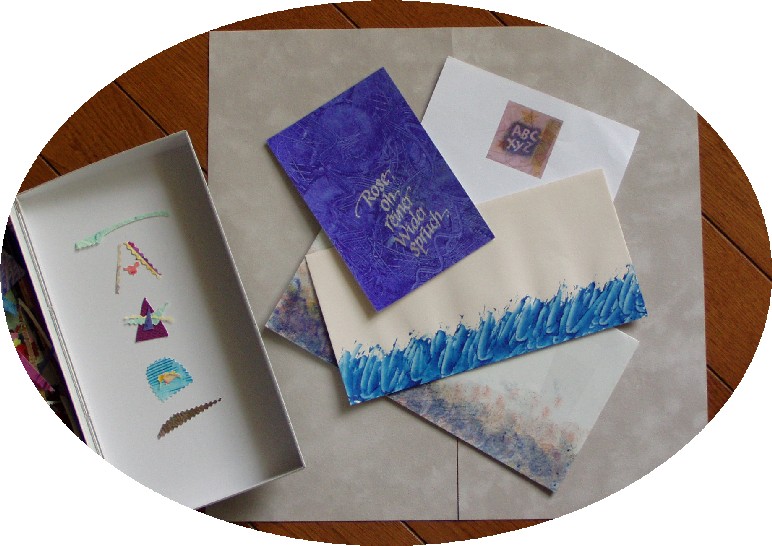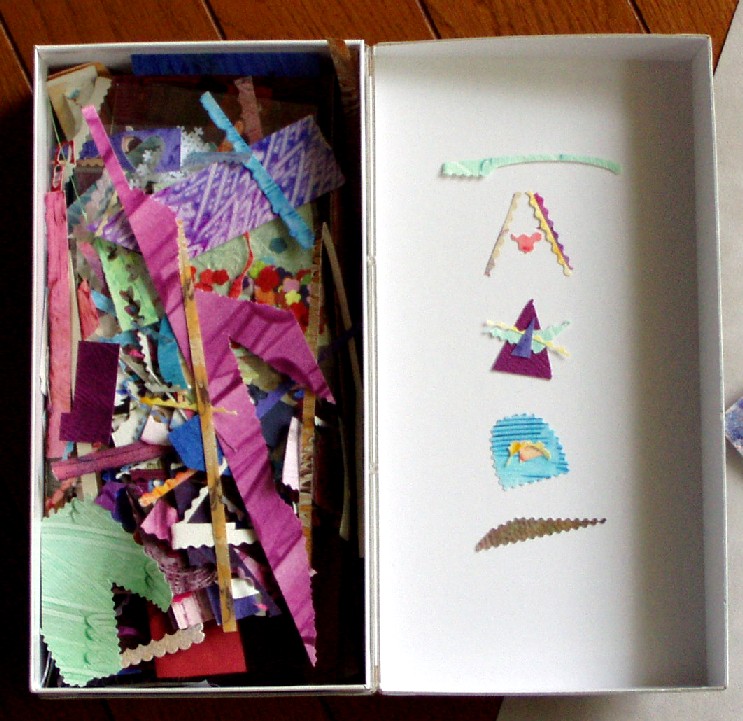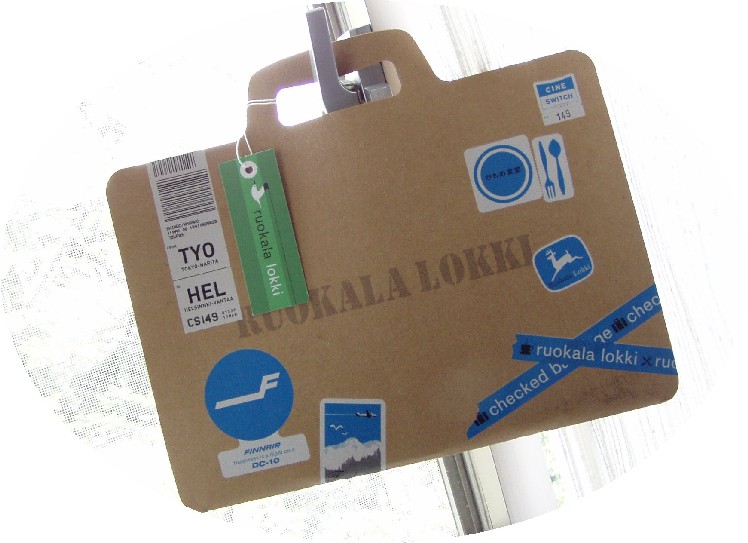
ペーストペーパーの運命
mojitor-sさんのWSでも人気のペーストペーパーですが、これが一度作ると切り刻んだ破片までも捨てられない・・・というある種問題が起こります・・・。
収納の達人は「一年使わなければ捨てましょう」などと捨てられない人間の肩を「ポン!」と叩いてくれるわけですが・・・ペーストペーパーやら水彩ウォッシュした紙やらの破片は何年たっても「まだ使うかも・・・」的発想で眠らせておくことがおきるのですね〜。
破片たちは、とある箱に収められて日の目を見ることを待ちながら、たっぷりと睡眠をとっております。
熟成したからといって色味が増すとかはないのですが・・・たまに箱を覗くとすっかり忘れていた「あら〜、こんな模様作ったりしたのねぇ〜。」と懐かしくなってしまいます。
破片はポイントとして使ったりする運命を持ち合わせておりますが、ペーストペーパーはそれぞれの道を歩みます・・・。
アクリル系の絵具でしたら耐水性になるので、無味乾燥な封筒を華やかにすることに一役買うこともできます。余ったペーストの嫁ぎ先ですね・・・。また、ハガキ大の紙にペーストしてその後、プリントごっこで文字をプリントすればカードを大量生産できます。ちょこっと楽したい方にお勧めです〜!またペーストペーパーを撮影したり、スキャナーで取り込めば、その後ステーショナリー関係に使用できますね・・・。
作品にも小物にもいろいろ使えます・・・ペーストペーパーの運命はあなたが握っているのです!
「りんごは赤じゃない」
ほめる教育について書かれた本だというので、子どもをほめて育てたいと思っているのに実行できない私はそういう不純な動機で手にとってみたのです。
ふつうの公立中学校で美術を教える太田恵美子先生、カリスマ教師と呼ばれ数々のコンクールの受賞者に教え子がずらり・・・のルポ。なんだかすごい先生の特別なお話なのかしら、と思っていましたら。
「りんごは赤じゃない」のタイトルが示すとおり、思い込みで色を扱わないようにする、
画材は絵の具に限らずクレヨンなどいろいろなものを使う(学年があがると絵の具しか使わないような指導になっているそうです、確かにそうだったかも)
教室に早く来ただけで「いい子」とほめる、
ポケットマネーで美術室を美しく飾り居心地よくする、などなどなど。
もちろん簡単には真似できないけれど、なるほどなと思わせるお話がたくさん出てきます。
生徒たちはよーく観察してスケッチを描き、先入観を取り払って野菜のレプリカをつくり、自分自身と向き合ってテーマを掘り下げ、と少しずつ力をつけていきます。
美術の技術的なことだけが重要なのではなく、理想の教育とかいうことでもなく、「自分の人生」を大切に思えるようになる。読み進むうちに不純な動機で読み始めた自分が恥ずかしくなってしまったのでした。
スピードボールC-6
カリグラフィー用のペン先はいろいろありますが、皆さんはどういう種類をお使いですか?
人によって好き好きはあると思います。主なメーカーは、ミッチェル、ブラウゼ、スピードボールですが、私は文字のサイズ、文字の太さ、書体、使用する紙の質、書き方などによっていろいろと使い分けています。
大きな文字はスピードボール、柔らかい線、細い線を出したいときはミッチェル、プレス+リリースで筆圧を使って書きたいときもミッチェル、小さい文字をき ちんと書きたいときもミッチェル、速いスピードですいすいガンガン書きたい時はブラウゼ、小さいビルドアップもブラウゼ、フローリッシュもブラウゼ、など など。
ミッチェルとブラウゼは良く使いますが、スピードボールだけは、大きなサイズにしか使いません。それも、シャープな線が出にくいので、ペン先の厚みを薄くなる様に、アーカンソーストーンで削って使っています。スピードボールには、大きな文字を書くしか使い道がないと思っていました。
さっそく伊東屋へ行って購入して書いてみました。
ほんとでした・・・・
驚きました。ほそーい線が書けます。ミッチェルの様に両角が鋭くないので、紙にひっかかる事もなく、インク止めにたくさん絵の具が入るから持ちも良く、細い線がスイスイ出てくれるので楽しく書けます。(もしかして、ブラウゼの0.5よりもいいかも?)
それにしても、既成概念にとらわれていると、良いものに出会えないんですね。反省・・・・・・
ピッタリくる使い道のある道具を、新たに発見できた事がとにかく嬉しいです。連休はこれを使っていろいろやってみよーっと!
刺繍のペンケース
カリグラフィー用のペンを持ち運びするのに、普通の筆箱には入らないので、ペンケースもカリグラフィーをするにあたってとても大事な道具です。
さて、画像は教室にいらしゃっているMさんのペンケース。
これを見て、教室中みんなビ〜〜ックリ!!目がパチクリ!
文字の部分がすべてクロスステッチで刺繍されています。色も文字の形も素敵です。伺ったところ、こういうキットが売られているのだそうです。
考えただけで、めまいがしそう・・・(昔は全然苦でなかったんだから、若いってすごい!)
こういう文字のデザイン、いいですよね。私にも作って〜とお願いしたらら、いいですよっておっしゃってくださいました。ほんと〜!?嬉しい!!
消しゴムスタンプ
銀座伊東屋のアネックスが新しくPaperとスクラップブッキングの売り場「Papierium」(パピエリウム)に変わったと聞いていたので、いつか行きたいと思っていました。
ちょうどカリグラフィーの道具を買いに行くついでに、と立ち寄りました。
売り場には、ハンドメイド魂をそそられる物ばかり!あまりじっくり見ると、よけいな物までまた購入してしまいそうだから、さささ〜っと回るしかない!
・・・が、こま けいこさんの「晴れ ときどき はんこ」という本と目が合ってしまいました。
紙だけでなく、ファブリックにスタンプしたり、雑貨との組み合わせが妙に可愛い!こういうのめっちゃ好き!・・・ってことで即買い。
以前消しゴムスタンプ作りにハマった事がありました。慣れるとすいすい簡単に作れるし、カードや封筒のデザインに使って楽しいのです。日本には「はんけしくん」という優れたスタンプ用の消しゴムも売られていて便利。スタンプを押す時のいろいろなテクニックもあって、結構深い世界なのです。
しかし、肝心の私たちのカリグラフィー用具が、以前の画材売り場からこちらへ移り、縮小された感じだったので少々がっくり。悲しくなりました。いつかなくなってしまうのでは・・と危機感も・・・・。
いやいや、手書きの文字は不滅です。ですよね!
かもめ食堂でコーヒータイム
フィンランドでのロケ、さらに日本食堂が舞台という設定に、かねてから観たいと思っていたのでした・・・。
さてさて、映画の方は・・・やっぱり期待、否、期待以上に面白いお話でした〜。小林聡美、片桐はいり、もたいまさこの三人の他は全てフィンランド人という配役・・・。特にマリメッコを着こなしたもたいまさこさんの雰囲気、演技はもう圧巻でした〜。私はアメリカ映画のように勧善懲悪、大作・・・よりも淡々と綴られる映画の方が何となく気に入ってます。だから、北欧やドイツなどのわりと目立たない映画が好きです。
そして密かに?話題になっていたのが、この映画のパンフレットです。左上の画像のように旅行鞄の形になっているのです!ねぇ〜イケテませんか?鞄はこの映画の中でも結構重要なアイテムとなっていました・・・。当日は買うの忘れてしまい・・・他の友人が観に行くというので買ってきてもらったのでした!
今年は東京都庭園美術館でもフィンランドのアラビアの作品が展示されていますねぇ・・・。こちらも足を運ばねば・・・。
素敵な映画を観たあとは・・・何だか夢心地・・・。
たまには大切なカップでコーヒーでも飲みながら未だ見ぬフィンランドの風景でも想像してみようかなぁ〜。こちらはスウェーデン人リンドべりのカップです。昔の西武の包装紙もデザインしてましたね。現在製造されていないので、いつも利用している北欧ものを扱っているお店に入荷されたときに一客購入しました。(というか一客しか購入できませんでした・・・)
フィンランドというと・・・今までは、ミカ・ハッキネン、キミ・ライコネン・千湖ラリーとか・・・なぜかカッ飛びものに興味が偏っていたmojitor-h
試し塗りから何か生まれる?
何か書いて(描いて)いるとき、そばに置いた紙にペン先からのインクの出ぐあいを試したり、筆に含ませた色を試したり、しますよね。
そんな紙がたくさん出来て、まあ、普通は捨ててしまうのですが、ときどき、「あ、この色とっておきたいな」とか「このグラデーションがステキ」とか、書き終えた作品よりも試し塗りのほうがいい色に感じられます。同じ色を使ったはずなのに。
そんな捨てるにはちょっと惜しい紙の切れ端を壁に貼って、時々眺めたりして、「ひらめきの素」にならないかなあ・・・なんて。
何かが生まれるときもあれば、そのままゴミ箱にさようならのときもある。この頃はウェットなグレーに心ひかれております。
色のヒントはあちこちに。
本日の散歩の途中の「この色いいな」は野の花です。
紫から緑へのグラデーションがやわらかくてとってもすてき。たたずまいも清楚です。これ、なんという花でしょう?
遠くから見ているときはホトケノザだと思っていましたが、違いました。葉っぱがもっとしっとりしているのです。
ほんわりしていた木々の緑色が日に日に濃くなってきました。もうすぐ、五月。
太っちょ色鉛筆
mojitor-tさんがうっとりする色鉛筆の色見本を以前紹介していましたね・・・。それからSTABILOの色鉛筆を捜し歩き、ようやく手に入れたのが・・・なぜかこの太っちょ色鉛筆です!
店頭に並んでいる姿を見つけたときに「魅力的だわ〜」と感激したのですが、ふと「削るの大変かも・・・」という不安がよぎりました。
・・・しかし・・・それを見透かしたかのごとく近づいた店員さん・・・「これは専用の鉛筆削りもセットになっているんですよ〜」と微笑みながら説明してくれたのでありました。「なるほど・・・」と私。
右が太っちょ色鉛筆、左のフツーの色鉛筆との大きさがこんなに違うんです〜!
でも意外と握りが楽なんですね〜。太っちょさんの方が手には優しいかもしれません。
Saral
3月の終わりに新潟へ行った時、ジョイフル2でSaral(サラル)発見!!しかも、ロールだ〜!!!
サラルとは、ワックスフリーのトランスファーペーパー(カーボン紙)。何がすごいって、ワックスフリーだからトレースしたラインがケシゴムで消せるのですっ!
なんとも画期的な転写用の紙なので、私はアメリカでこれをみつけてからというもの、トレースにはこれを使っています。使用説明の所には日本語訳も書いてあ るので、日本にも輸入されているだろうと思っていましたが、探しに探して早10年!? 東京の大きな画材屋さんに行ってもみつからなかった物が、ナン ト〜!予期せず新潟で発掘したのでした。しかも安売りされていて980円が500円になっていました。うれしや〜
画像では白が行方不明のため写っていませんが、色は5色あります。濃い色の紙でもトレース出来てしかも消せる。なんてスゴイやつ!
ホ〜〜ントにおすすめの品です。